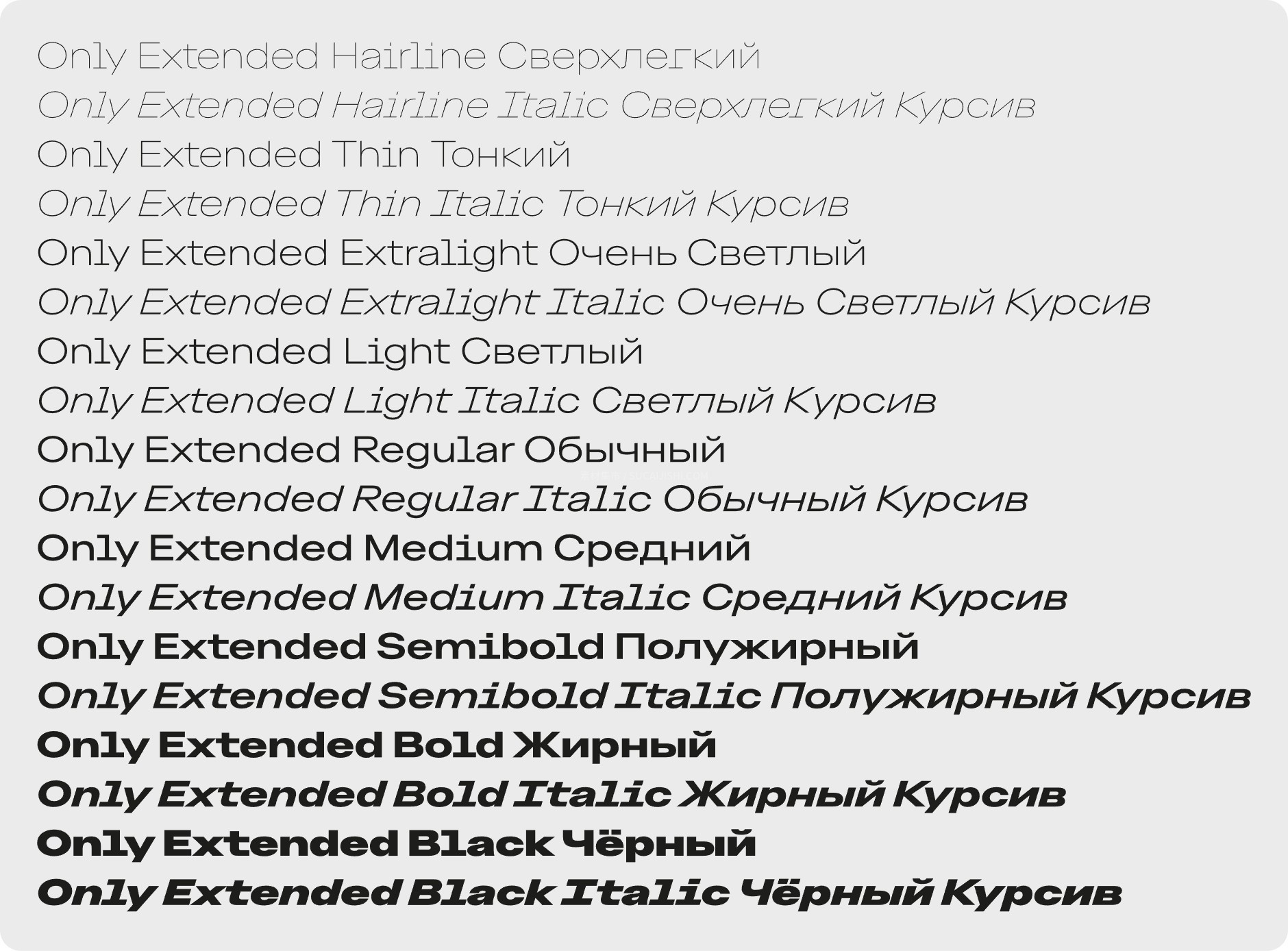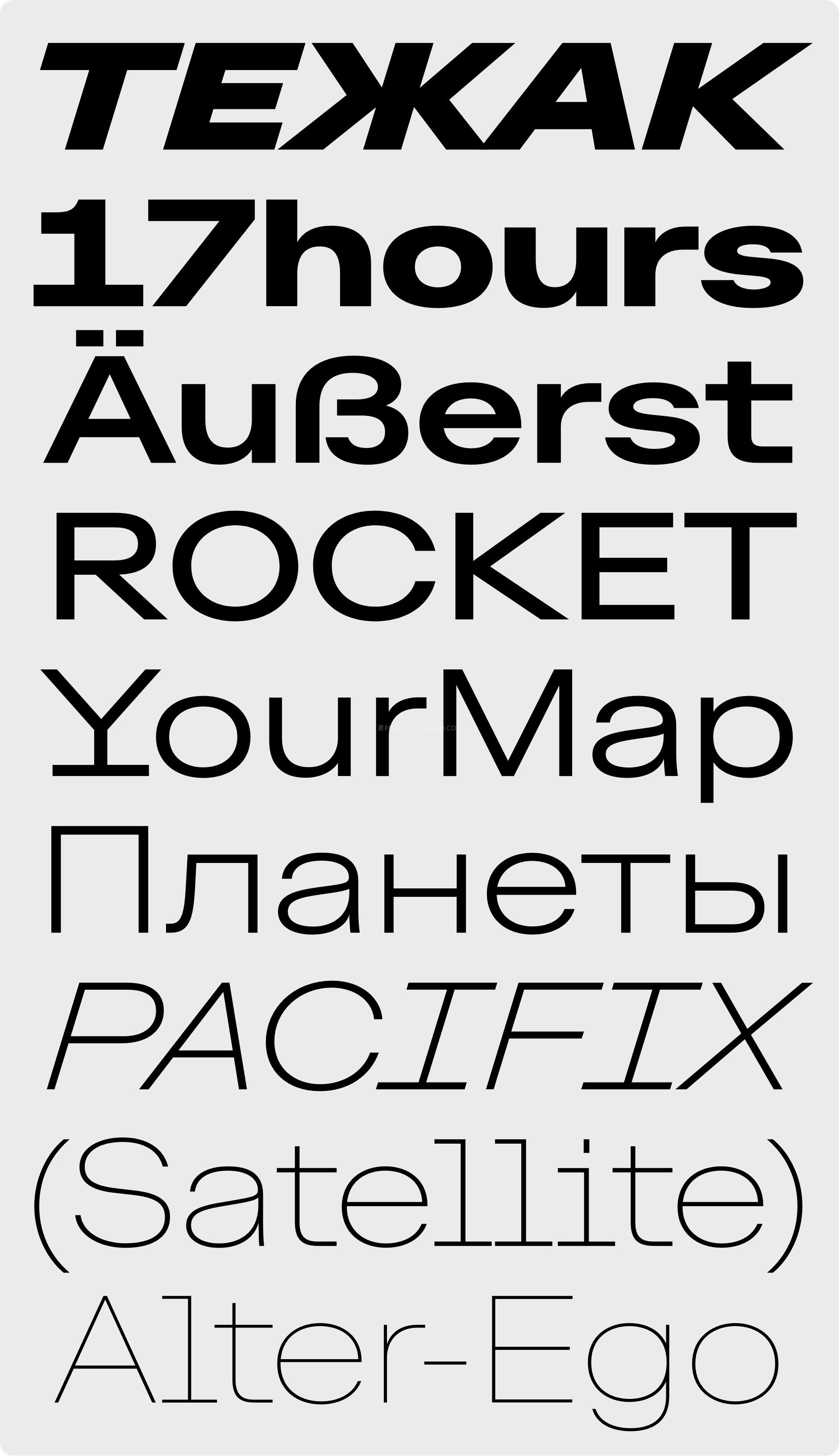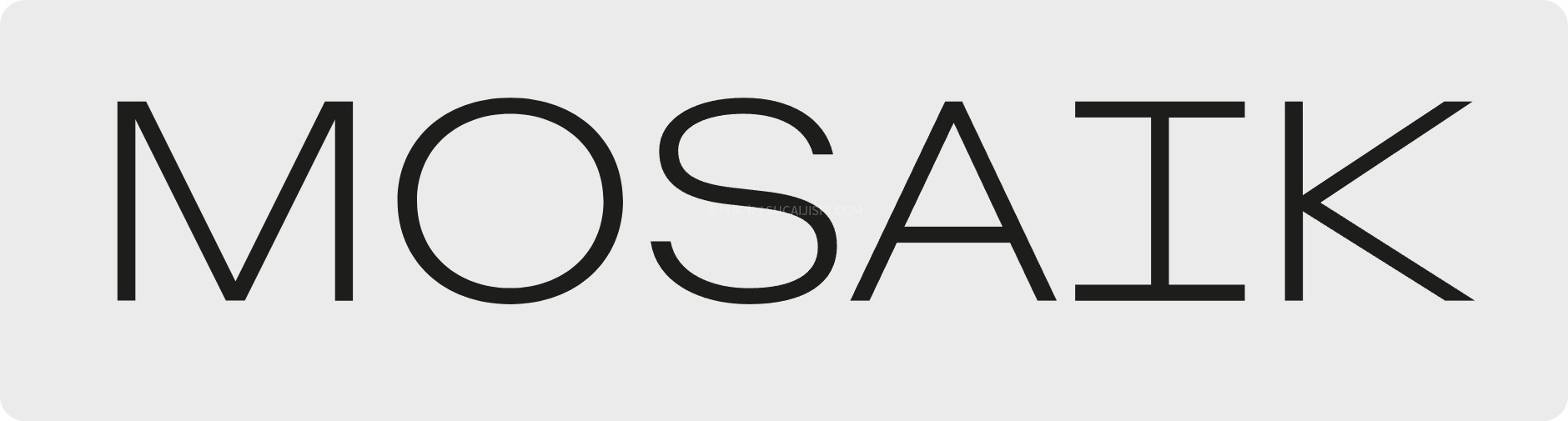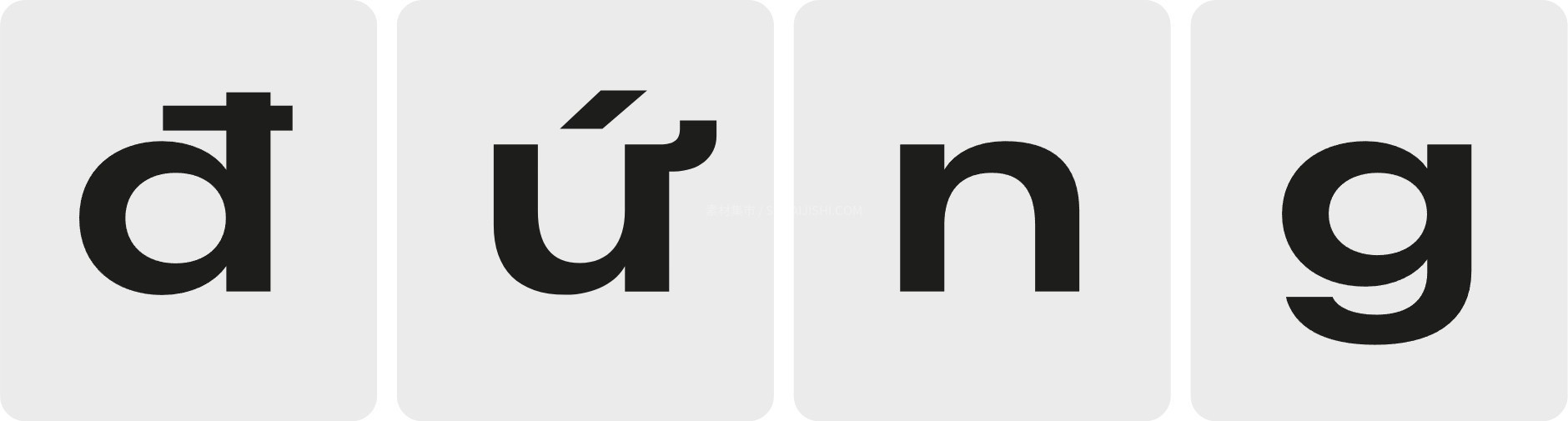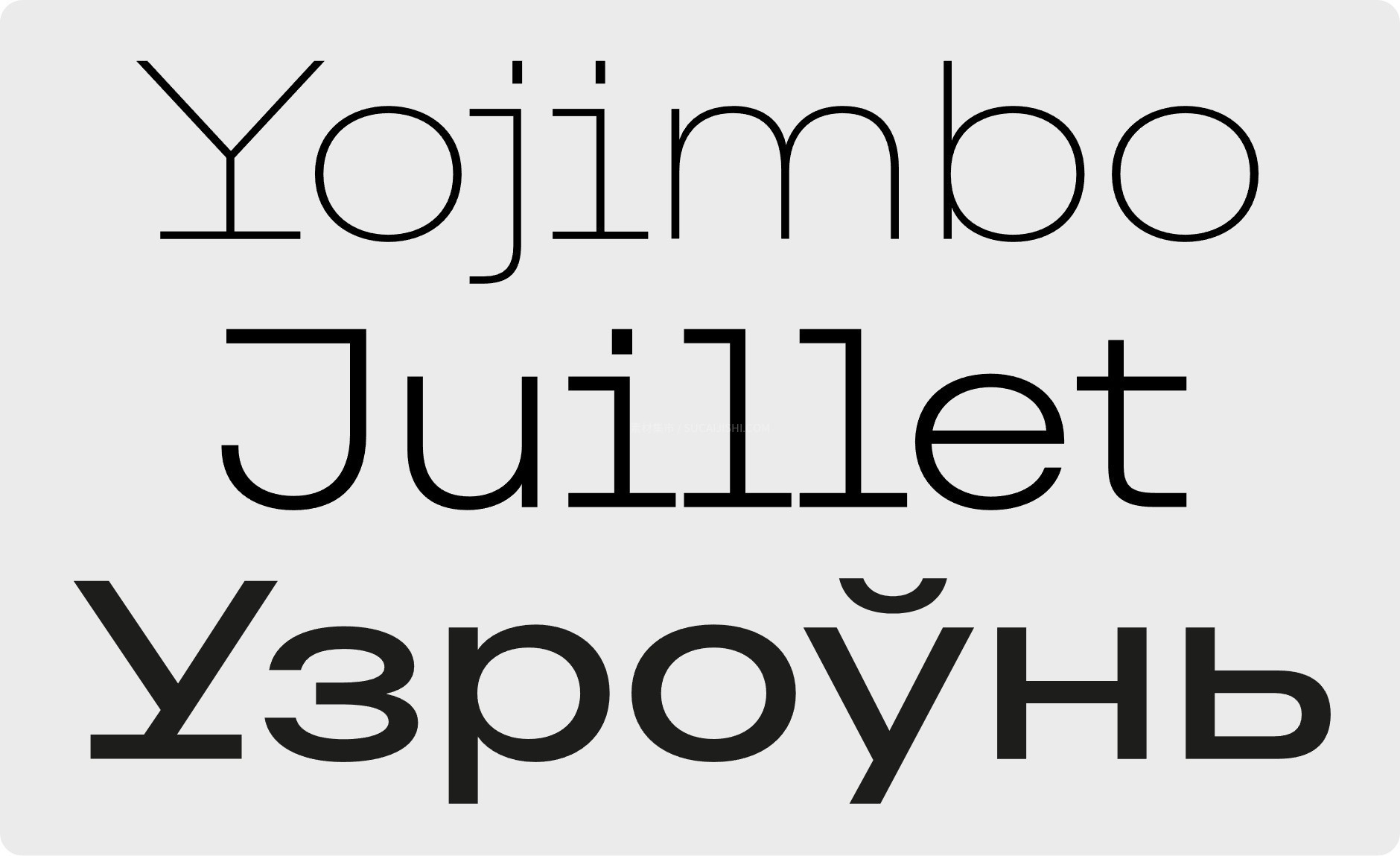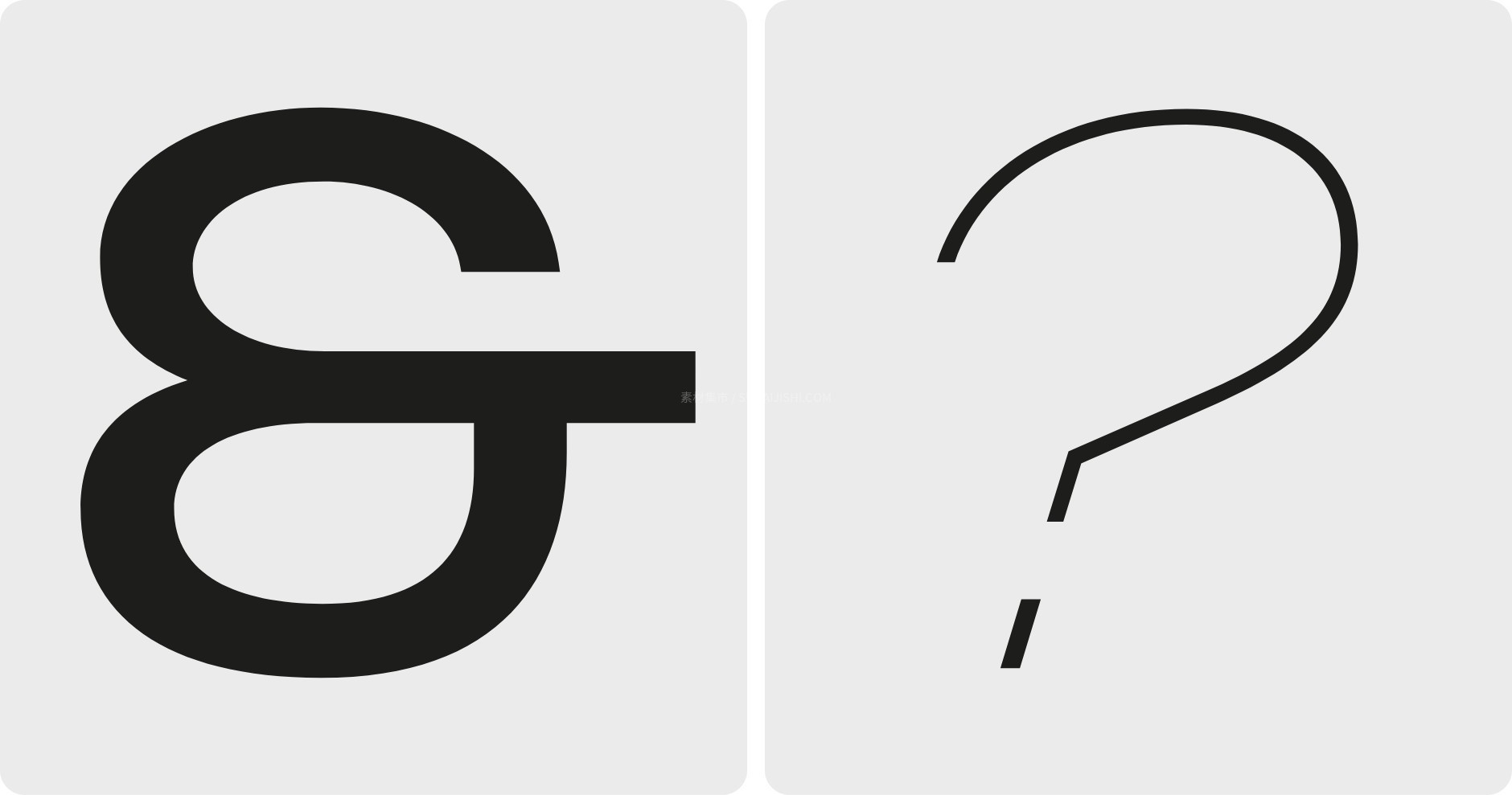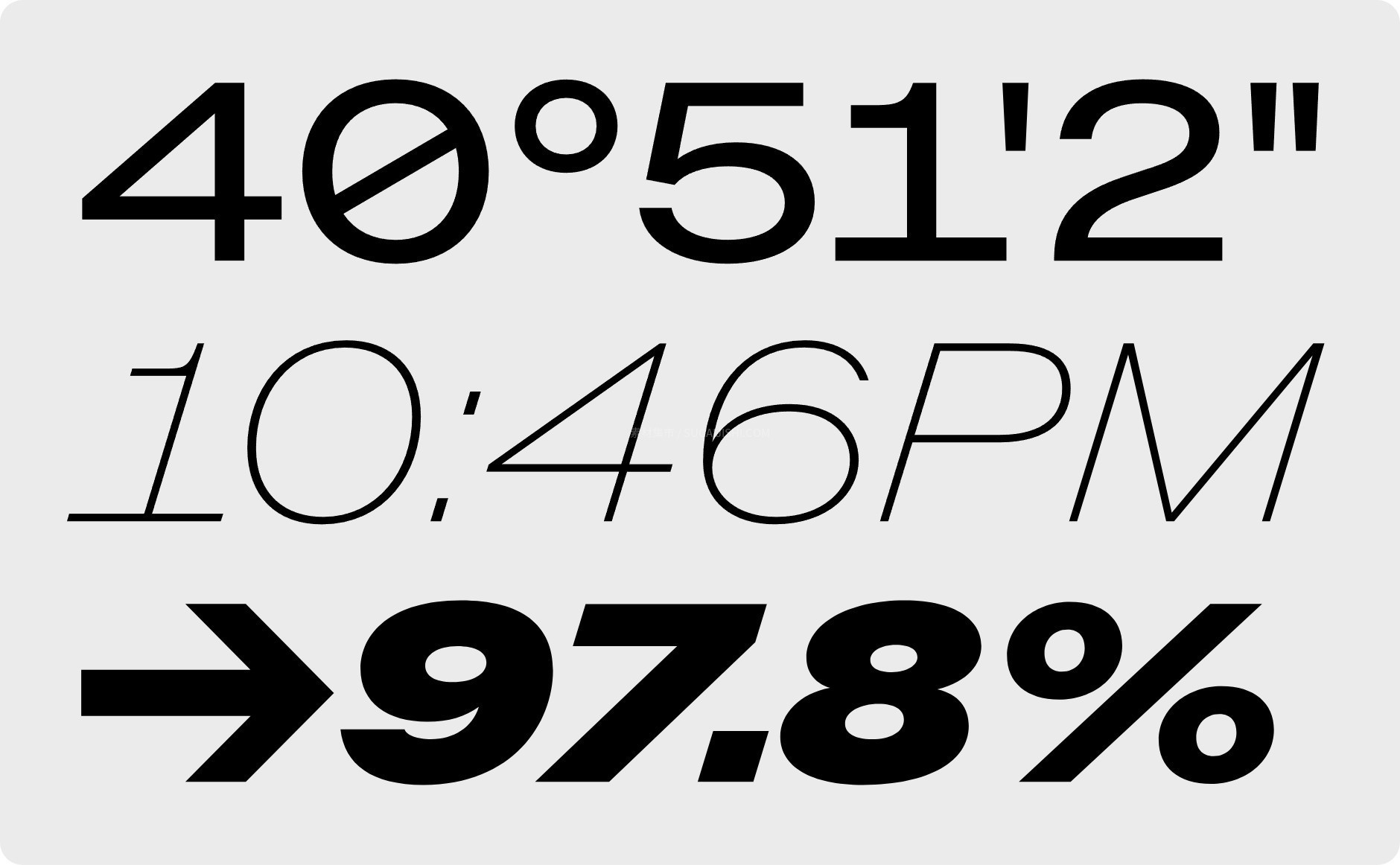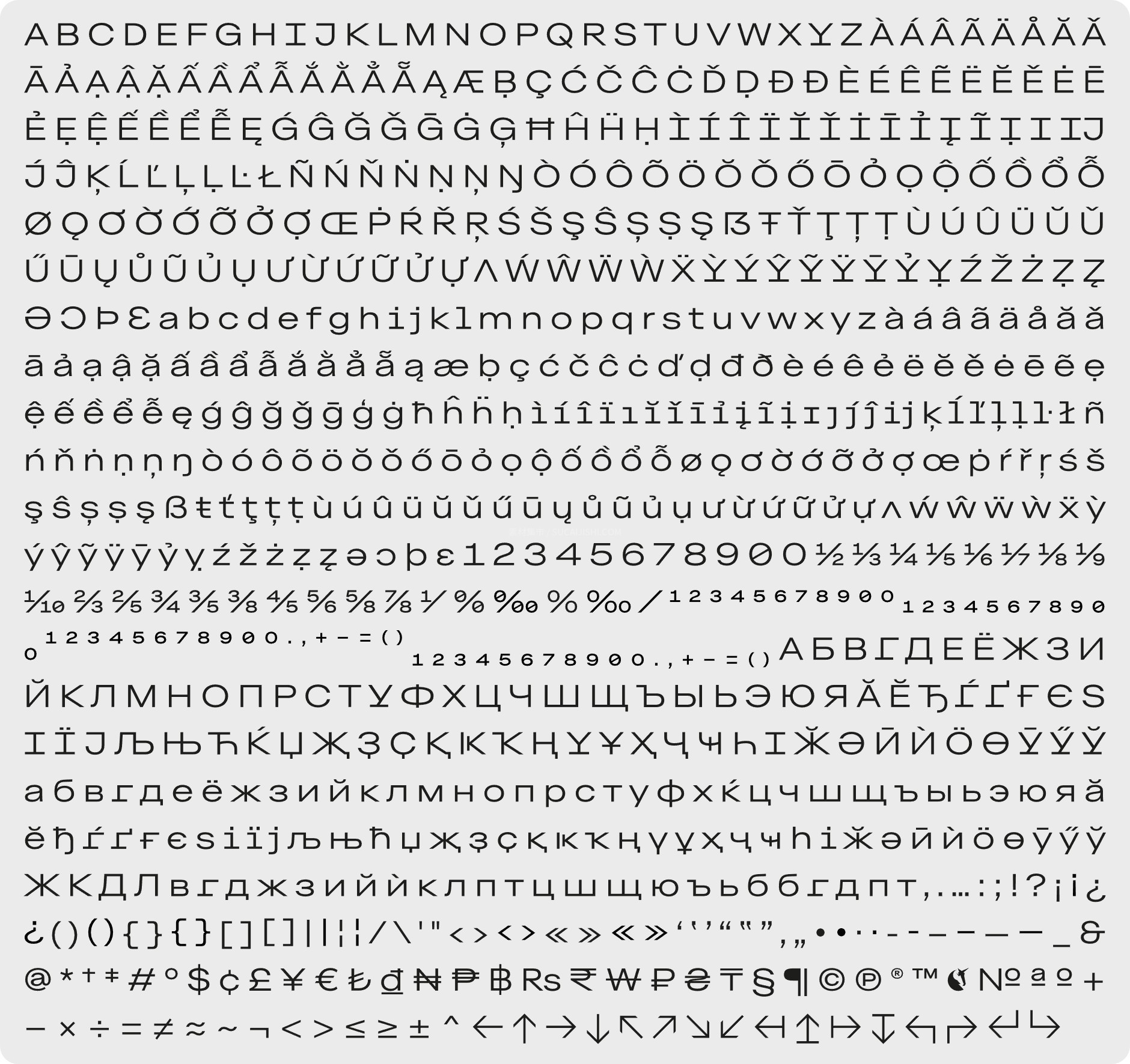
Only Extended 原生宽体可变字族 v4.000
这款专为“加长”而生的宽体字体系列,包含了 18 种静态样式及可变字体(Variable Font)版本。它提供从 Hairline 到 Black 的 9 种跨度字重及匹配斜体,并拥有原生西里尔字母与丰富的拉丁字符集支持(含越南语等少数语种)。其设计打破了常规水平拉伸的生硬感,巧妙汲取等宽字体灵感,为“I、i、j、l”等极窄字母加入特色粗衬线,在拉宽字形的同时保持了完美的视觉平衡与排版节奏,极具现代设计张力。